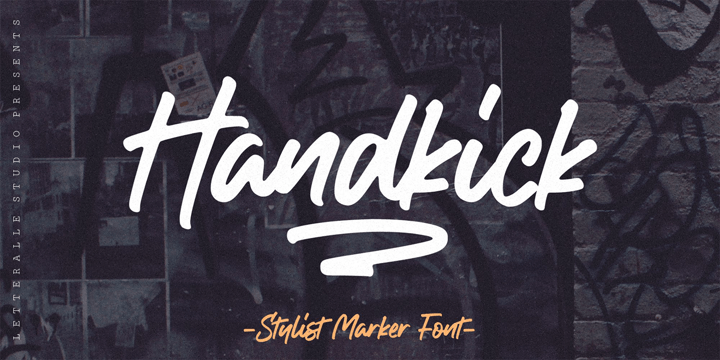
Myfonts Handkick Font
[Myfonts] Handkick Font
Представляем вам Handkick!
Гладкий и шелковистый рукописный шрифт. Handkick оснащен многоязычной поддержкой, лигатурой, а также подчеркиванием swash. Чтобы получить доступ к подчеркиванию, достаточно набрать "_1" - "_3". Handkick очень хорошо подходит для различных дизайнерских целей, таких как товары, упаковка, социальные сети, реклама, футболки, логотипы, мероприятия и многое другое.